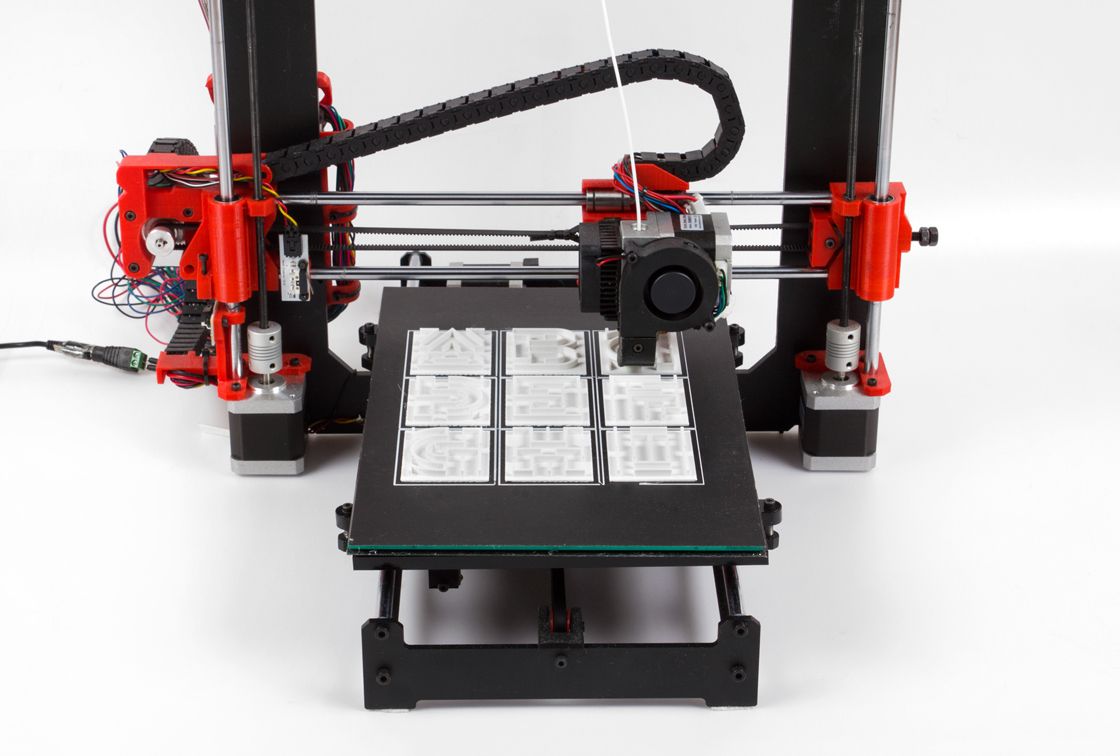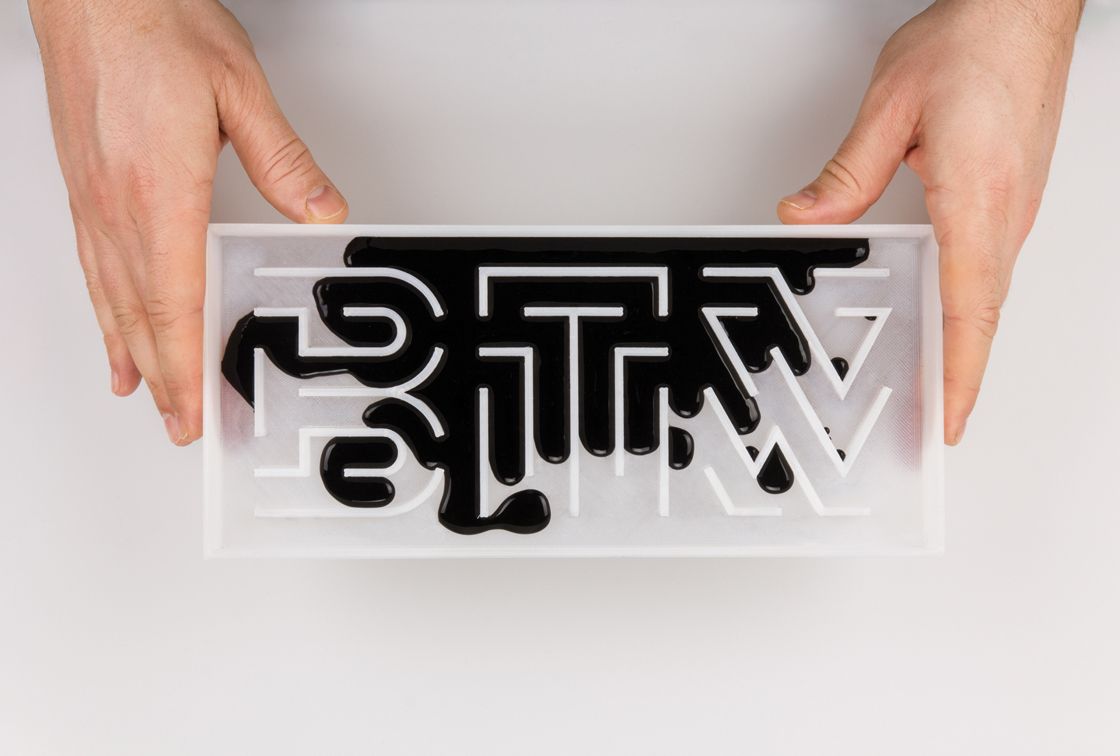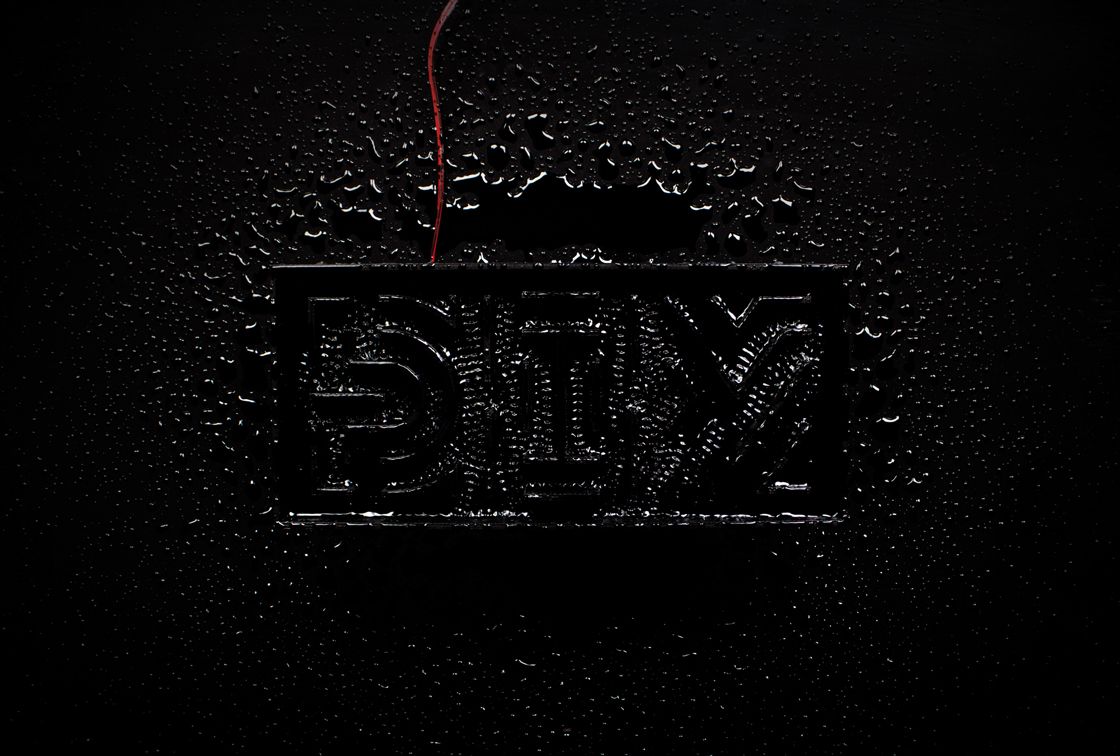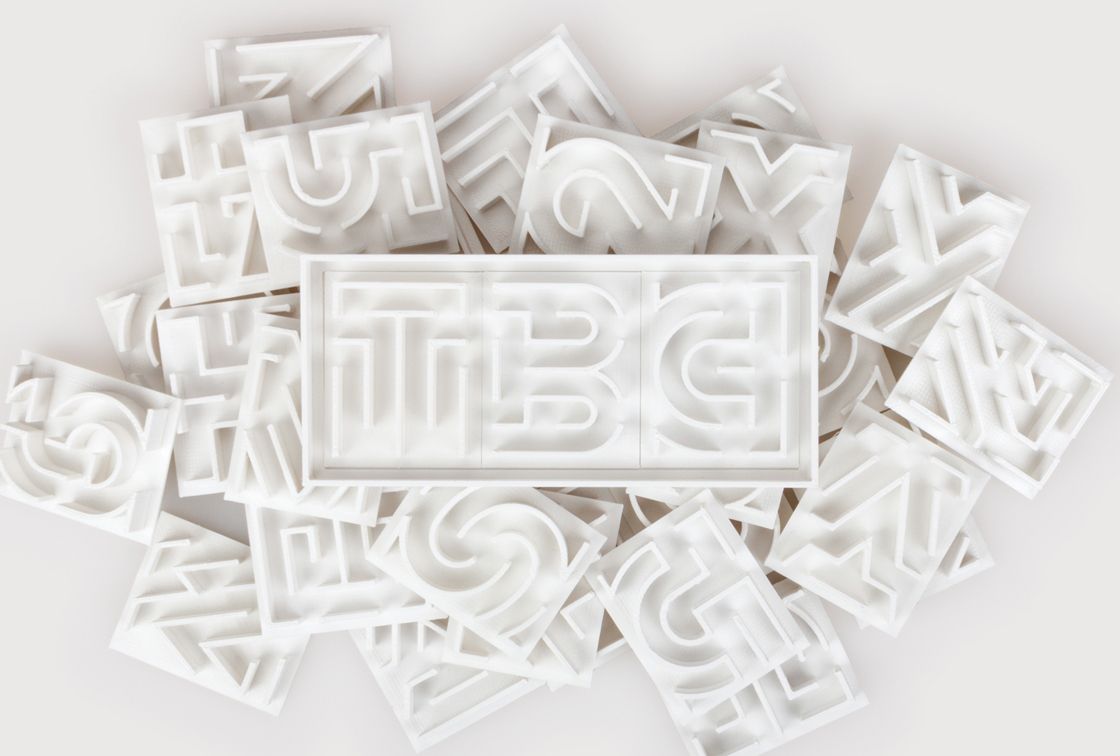
Tipografía y ciencia
Desarrollar una tipografía te da invariables posibilidades de experimentación. Al final el objetivo principal es que las letras sean legibles y puedan ser usadas para cualquier fin y aplicación. Aunque también siempre se puede ir más allá.
Bajo esta idea y la investigación química y física del comportamiento de algunos materiales Thomas Wirtz creó un sistema modular que consta de una serie de letras impresas en 3D que cobran sentido gracias a una variedad de procesos físicos.
El proyecto consta de un kit con sustancias que reaccionan con mayor o menor velocidad dependiendo de su reacción química y que al verterlas en el molde que conforma la frase "Take Your Time" ("Tómate tu tiempo") permiten la simulación analógica de la dilatación del tiempo (cámara lenta); efecto que sólo sería posible exclusivamente de forma digital.